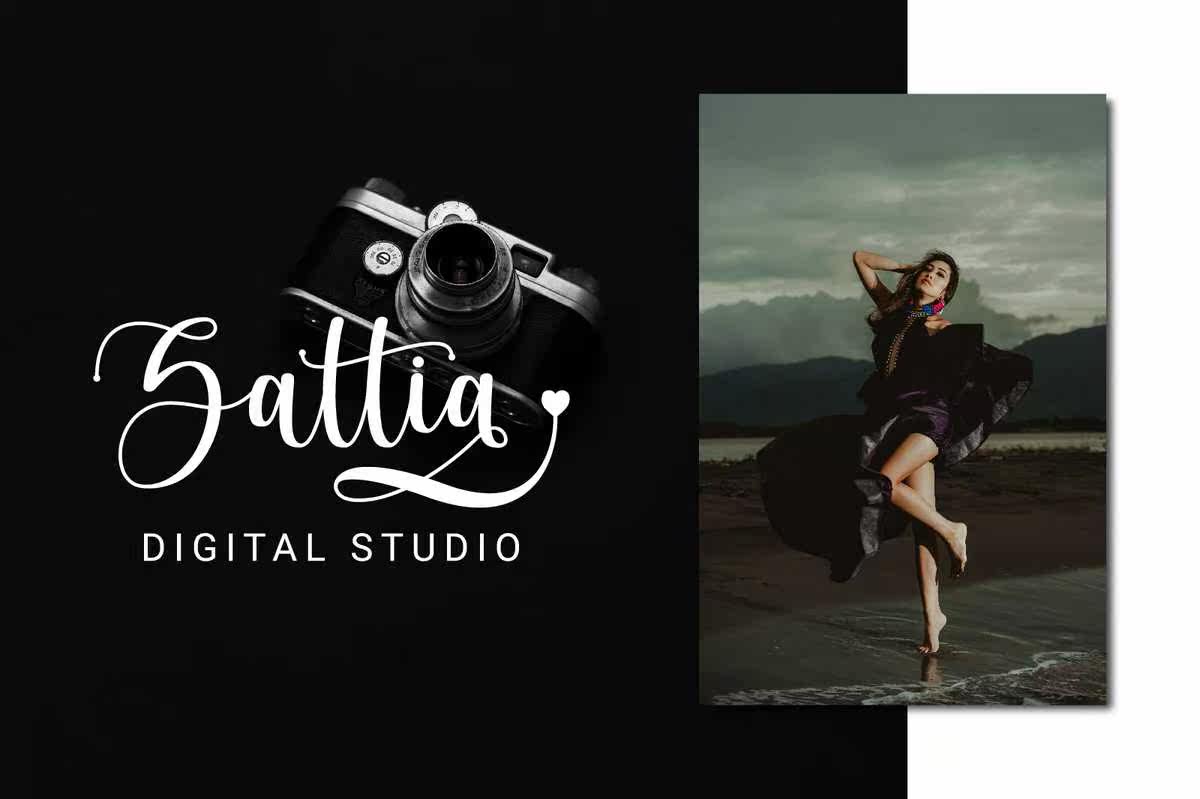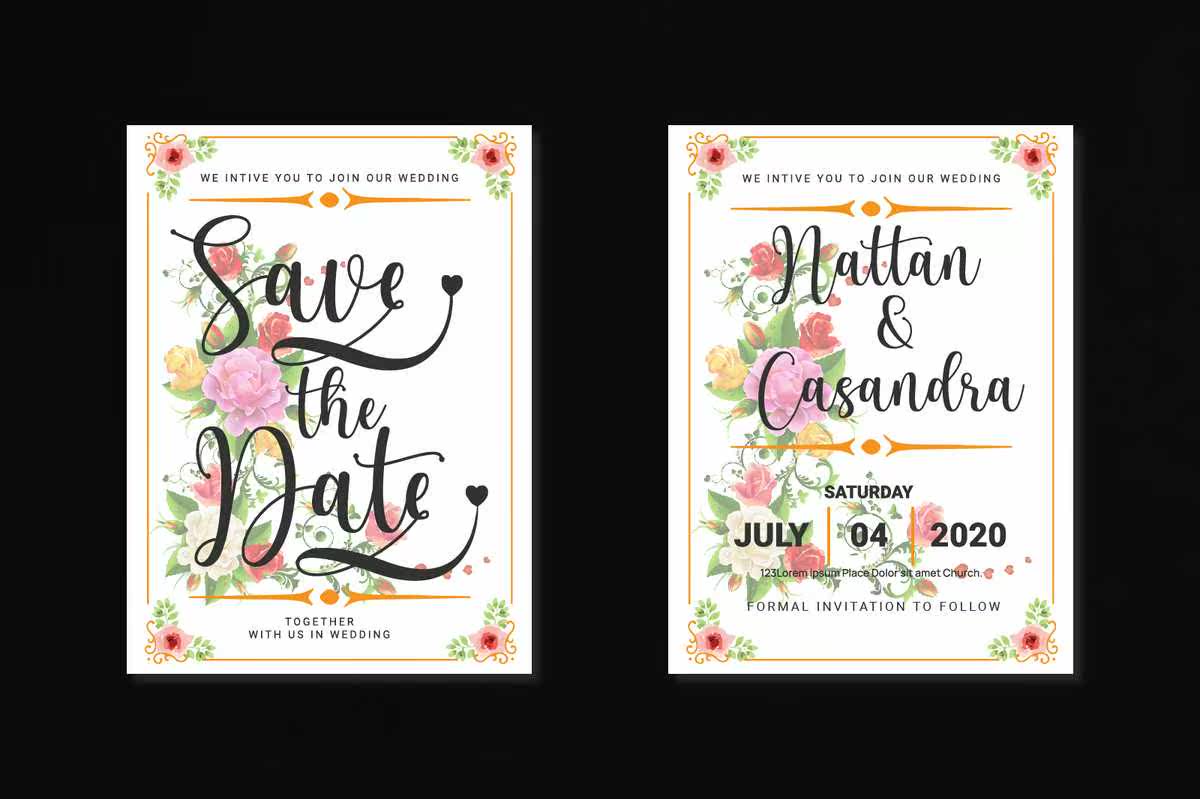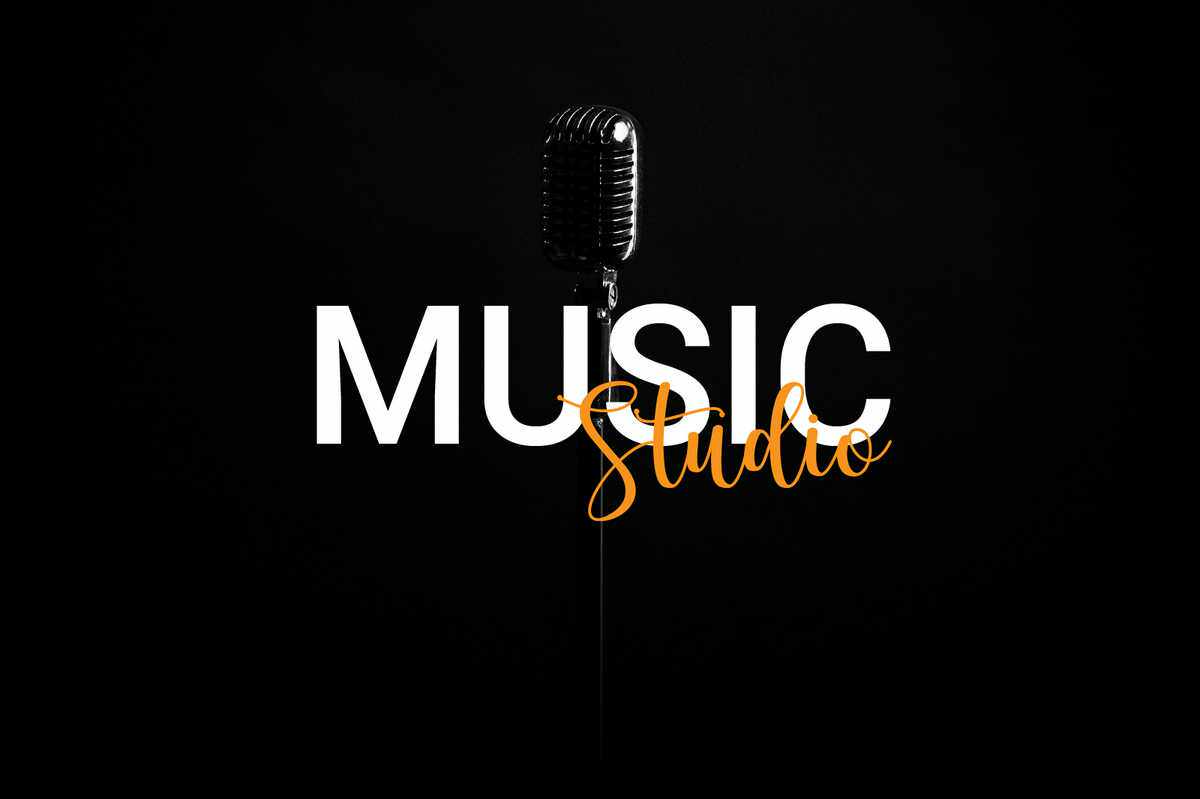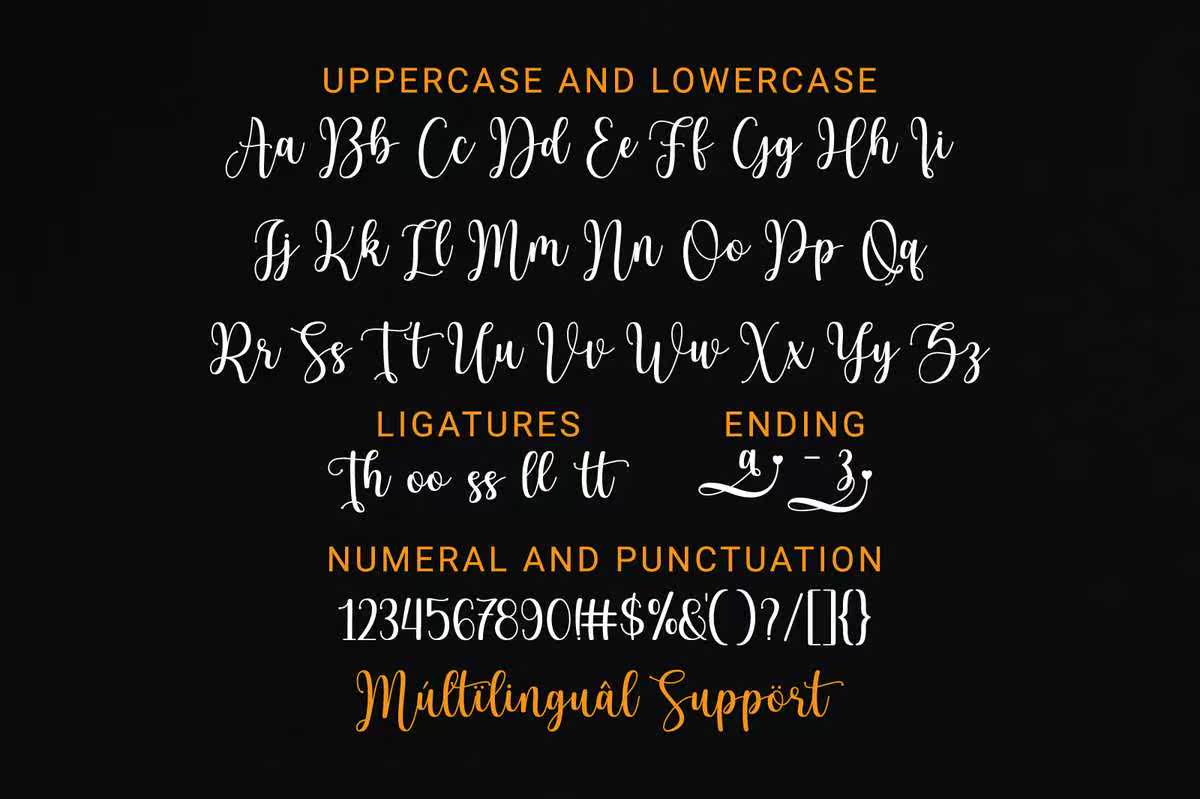
他的职业是一种与每个朋友都能感受到的优雅和优雅的手工风格。无论你是在寻找美丽的婚礼、美丽的艺术品、有趣的社交媒体和有趣的问候卡。他的职业也是一种可以让你的项目看起来现代、奢华和优雅的替代元素。这种风格会让任何创造性的想法变成一种工作屁!他的职业是一种与每个朋友都能感受到的优雅和优雅的手工风格。无论你是在寻找美丽的婚礼、美丽的艺术品、有趣的社交媒体和有趣的问候卡。他的职业也是一种可以让你的项目看起来现代、奢华和优雅的替代元素。这种风格会让任何创造性的想法变成一种工作屁!